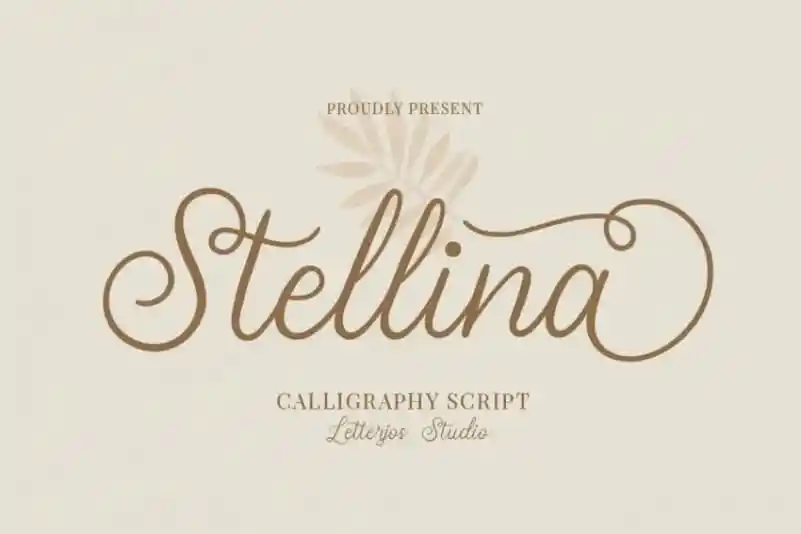
Stellina Calligraphy Font – Download Grátis
A Stellina Calligraphy Font é uma fonte perfeita para projetos que exigem elegância e classe. Ela foi criada pela equipe talentosa do 99designs para mulheres apaixonadas por design de gráficos. Esta font exibe um estilo sofisticado e refinado, adequada para uma variedade de aplicações como criação de marca, logotipos para casamentos, posts nas redes sociais, anúncios, embalagens de produtos, design dos próprios produtos, etiquetas, fotografia, marcas d’água, convites e materiais de estação. Ela é perfeita para qualquer projeto que necessite desse ar elegante e carismático. Experimente incorporá-la em seus projetos e veja como ela transforma a aparência das suas criações.